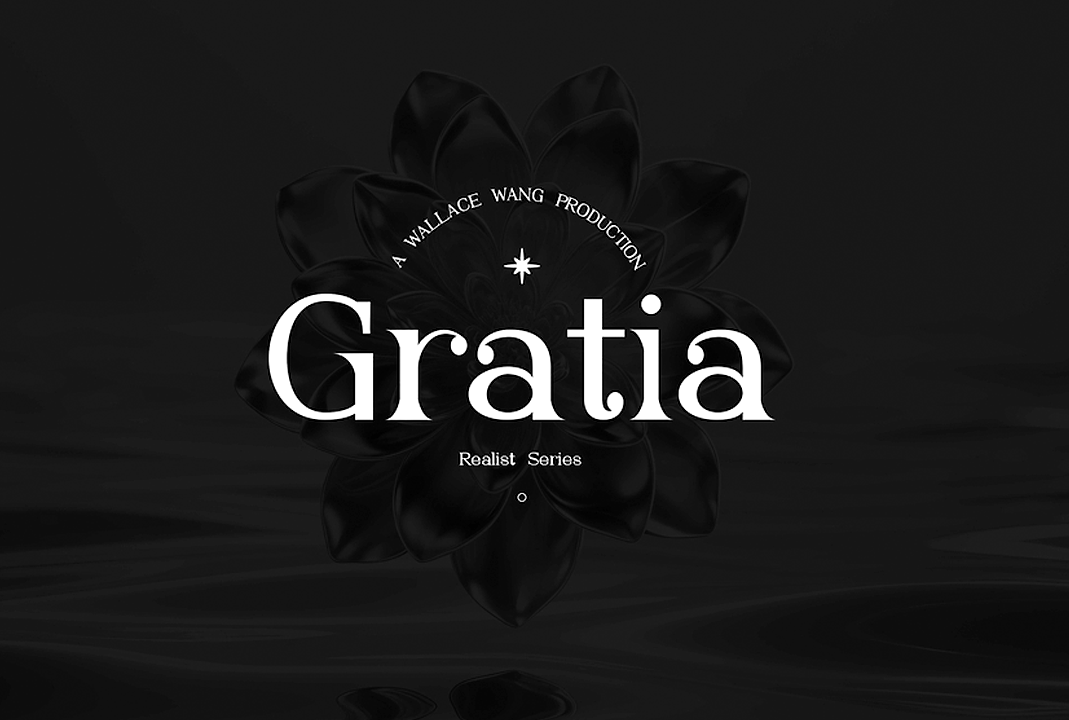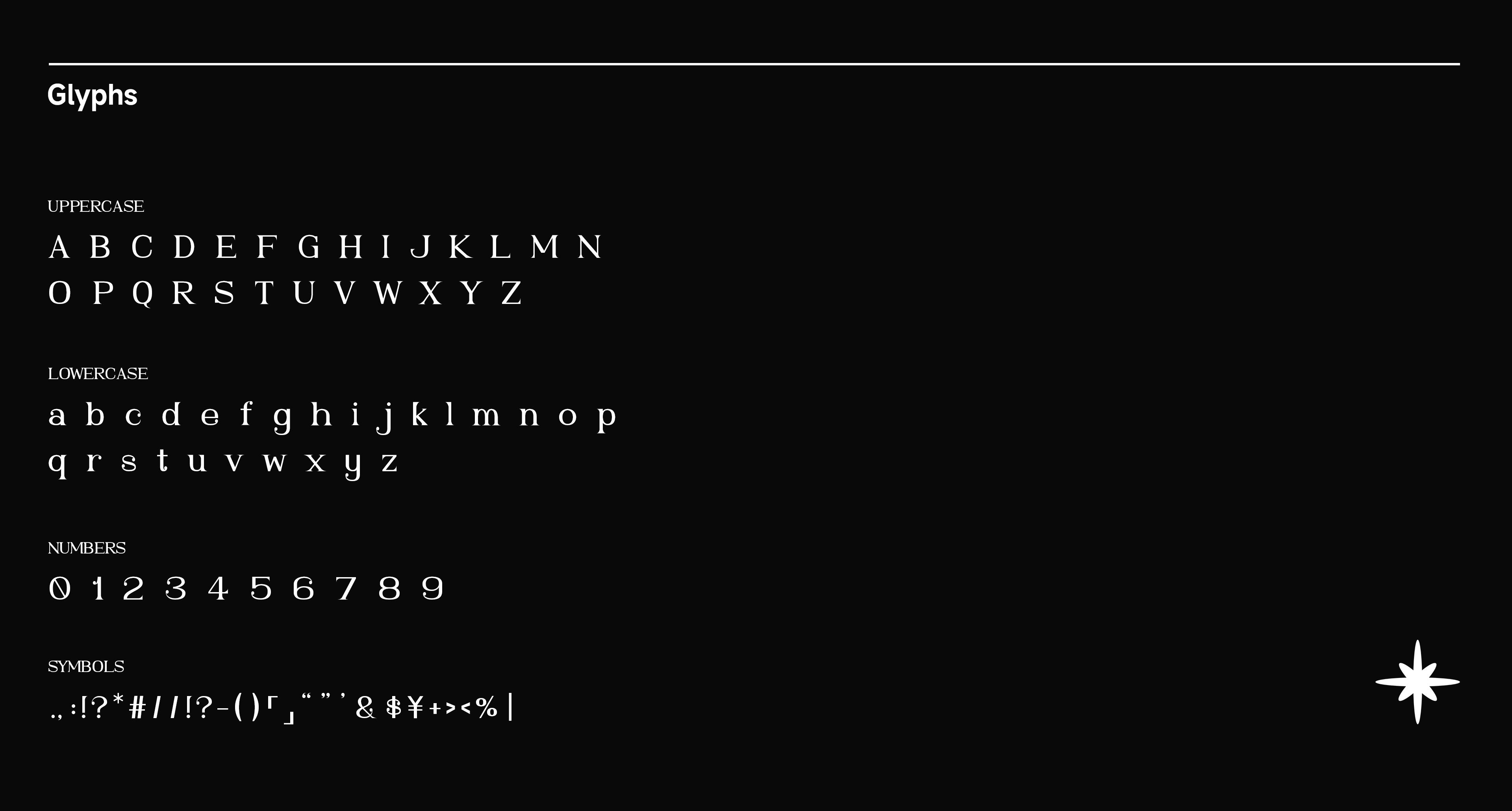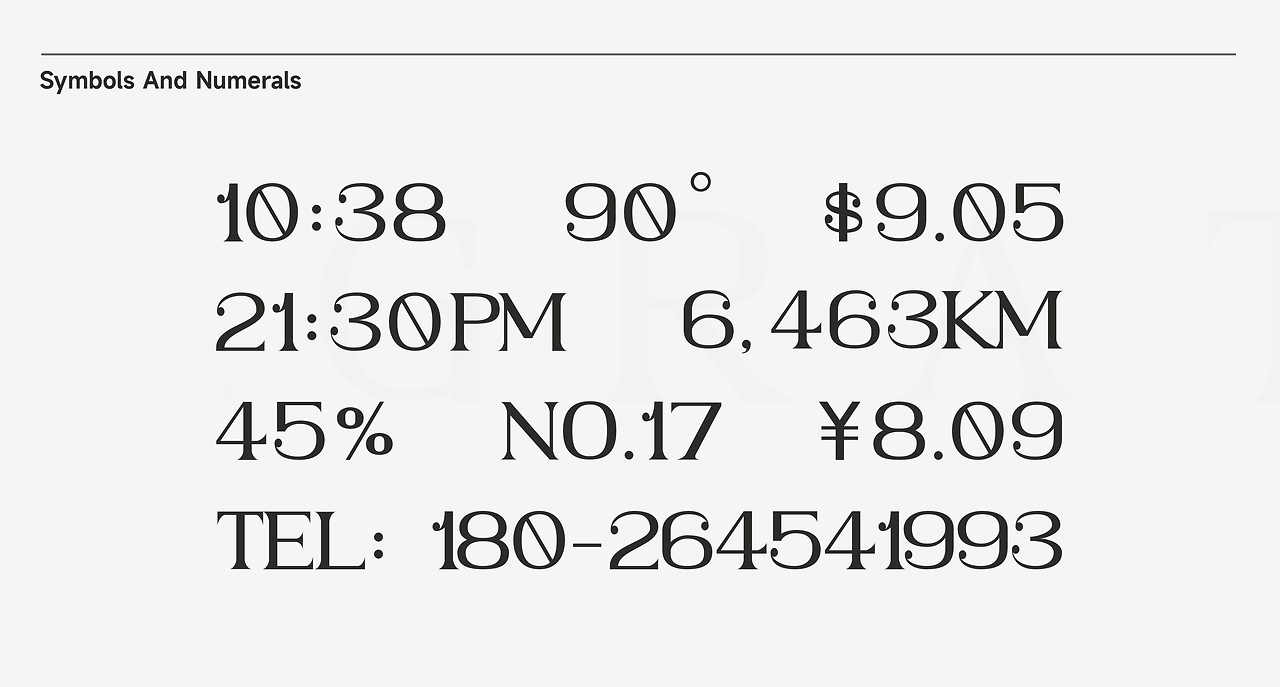
Realist Gratia Light 是由站酷设计师 WALLACE WANG(UID:16549726)设计的一款免费可商用英文字体。
Realist Gratia Light 字体字符观感复古经典,精雕细琢的字符曲线与吊坠配重设计。更适合进行大画面标题展示的优雅呈现字体。结合了现代的流畅干净的主流观感,打造的一款带有现代设计气息的优雅经典衬线英文字体。